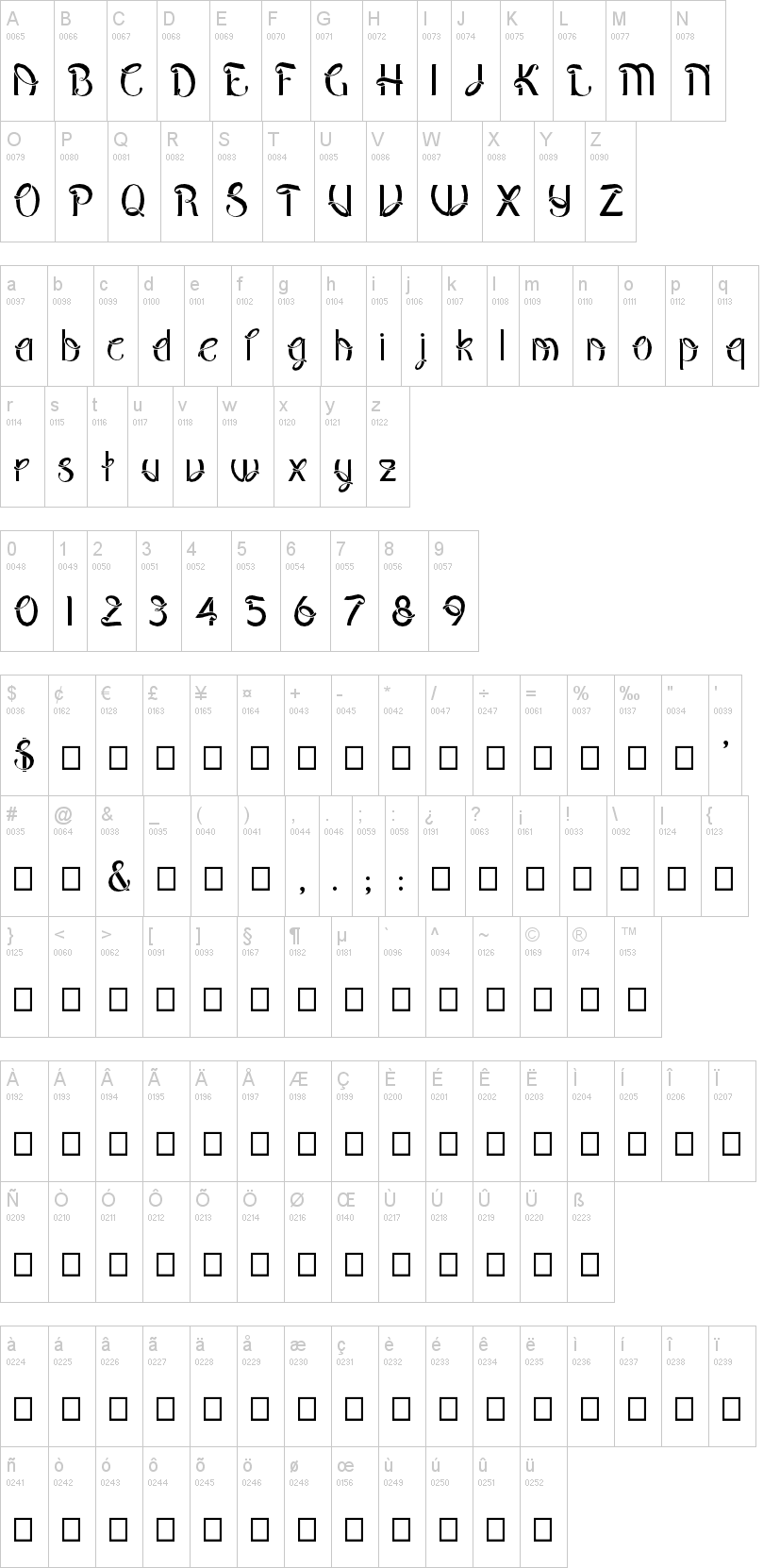
? Pepinot 字体是一款极具视觉冲击力的英文字体,它的设计灵感来自于20世纪30年代的早期插画风格。它的特点是粗犷的线条,平滑的曲线,温柔的色调,以及细节的处理,使它具有独特的美感。它的字体也拥有良好的可读性,能够清晰地表达文字的含义。它适合用于插画,海报,书籍封面,T恤,广告,海报等等。内容介绍
Pepinot是一款非常不错的手写艺术字体,具有很好的视觉感,适合于文化类的宣传设计、商业类品牌的广告和产品包装设计以及个性化文字排版等较多场景。